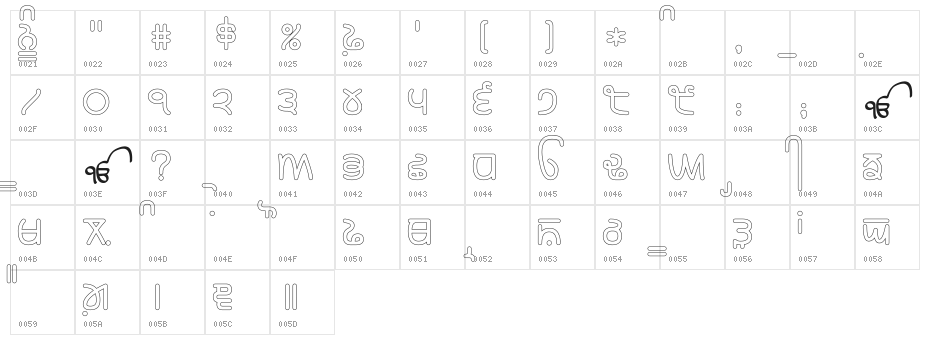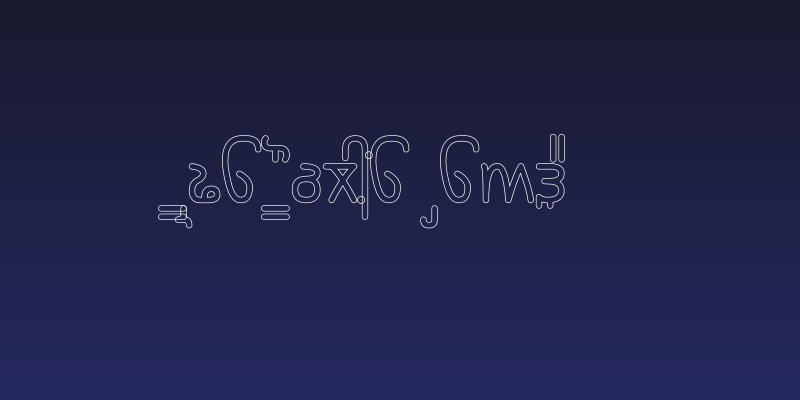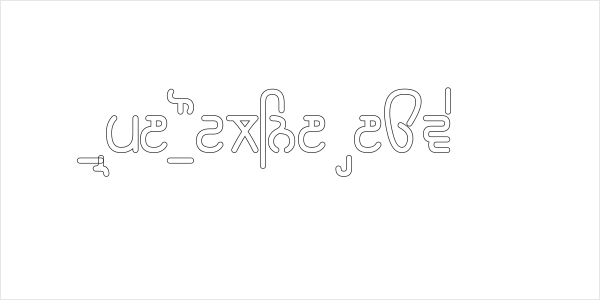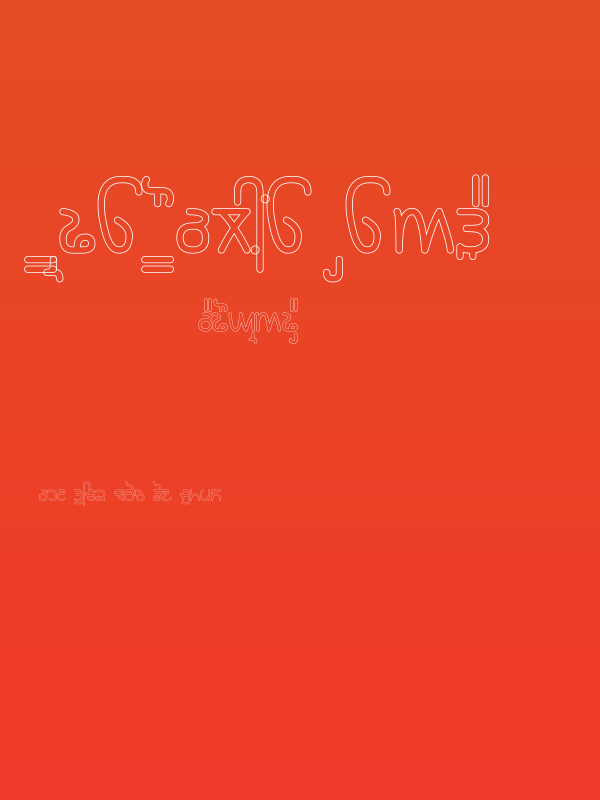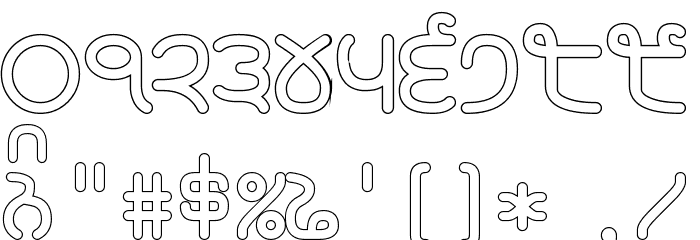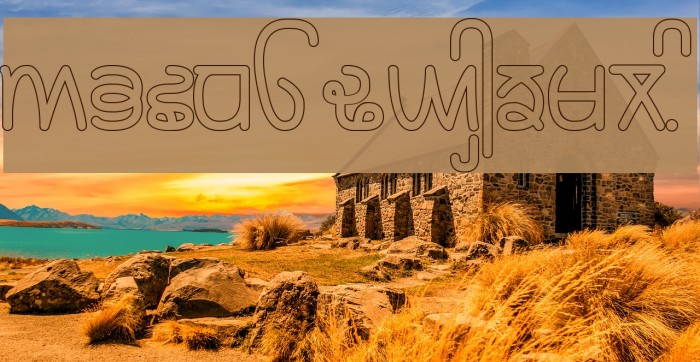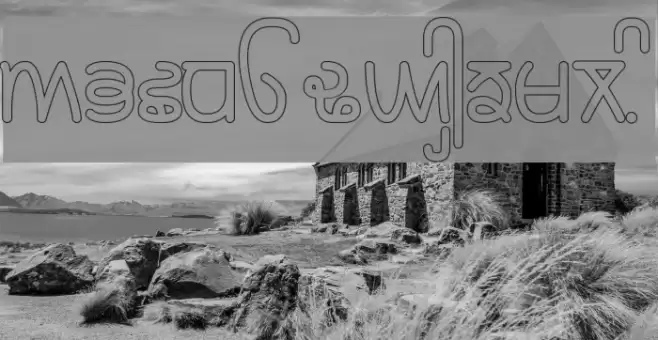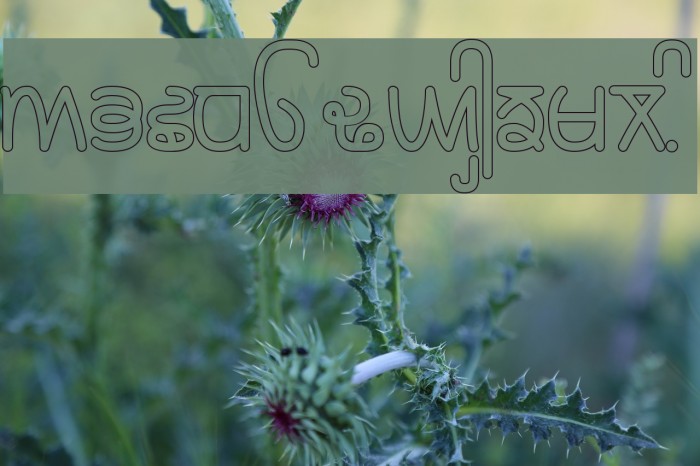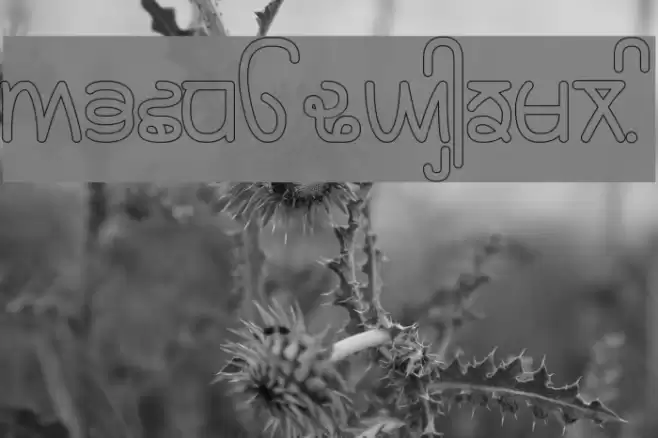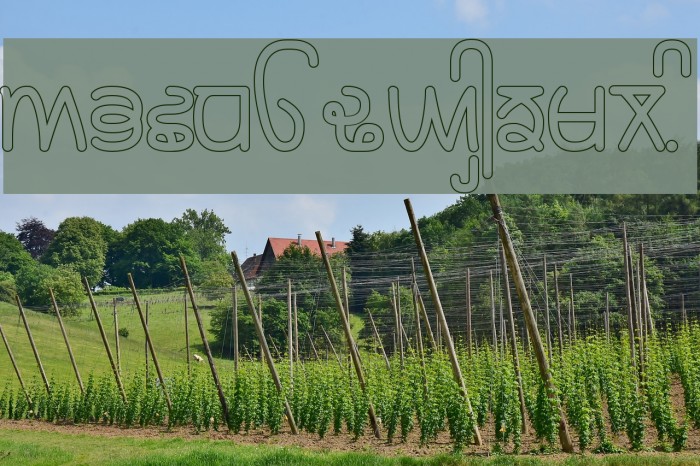
Rupe Outline Heavy Font
| Proiecte propuse | Ideal for branding, posters, album covers, and digital media where a striking, modern look is desired. |